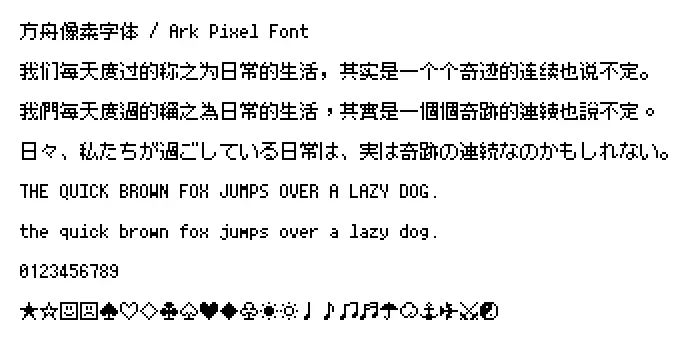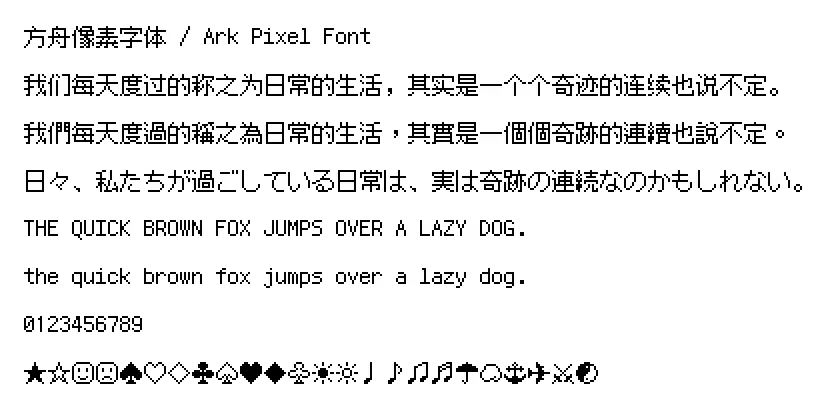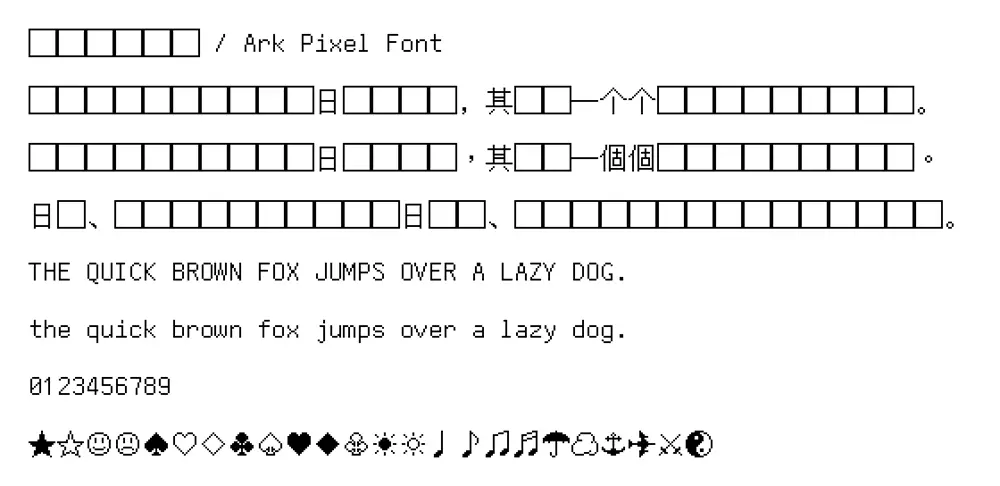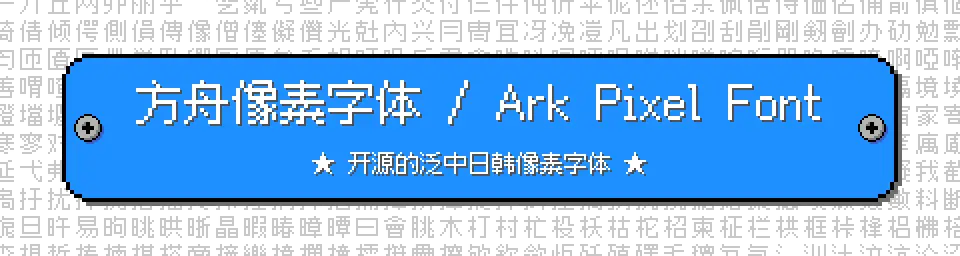
方舟像素字體是一款開源的泛中日韓像素字體,目標是為遊戲開發者提供一套可用於正文的開箱即用的像素字體解決方案,使用 SIL 開放字體許可證 第1.1版(SIL Open Font License 1.1)授權,
支持 10、12 和 16 像素尺寸,支持語言特殊字形:中文-中國大陸、中文-香港特別行政區、中文-臺灣地區、中文-傳統印刷、日語、朝鮮語 。
本字體目前還處於開發階段,所以還存在缺字,會持續更新,請查看Github項目主頁瞭解最新開發進度。